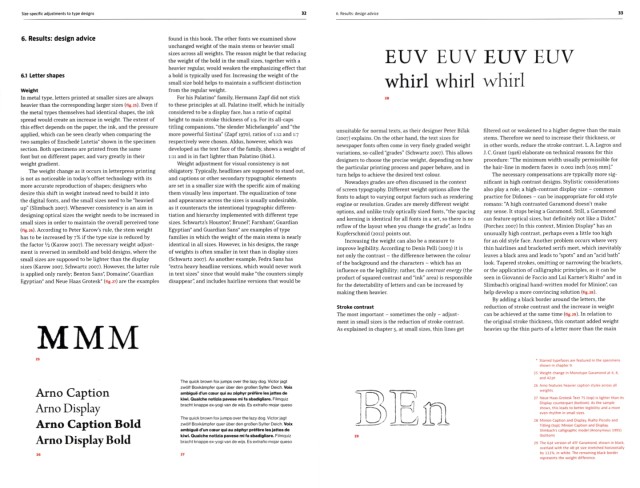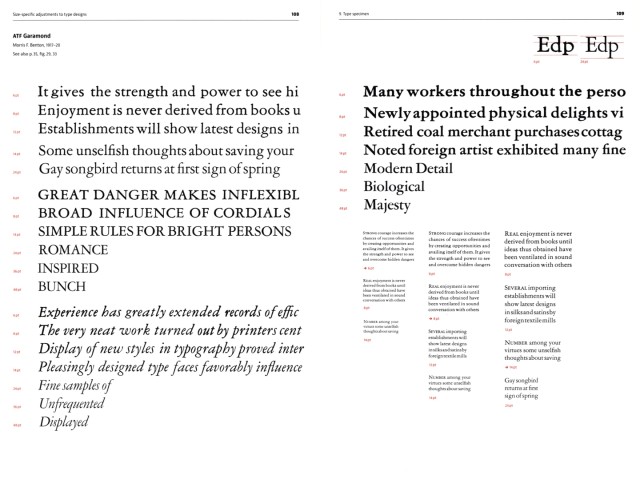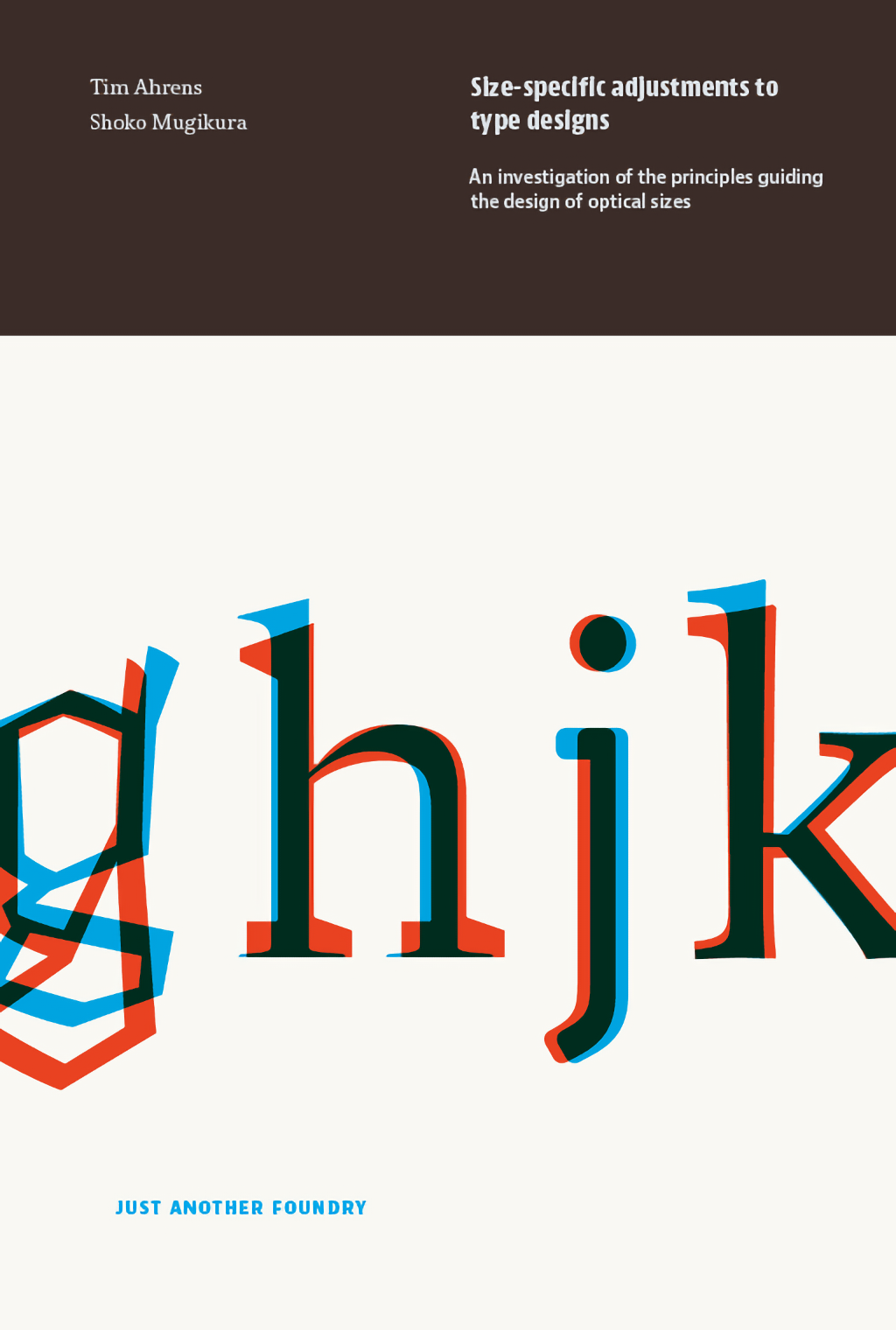
Size-specific adjustments to type designs
Autor: Tim Ahrens & Soho Mugikura
»Jest to nie tyle najlepsza, ale tak naprawdę jedyna znacząca praca na ten intrygujący i złożony temat«. [Thomas Phinney]
»Pomimo specjalistycznego tematu, materiał ten jest cenny nawet dla tych, którzy nigdy nie będą projektować liter ani uruchamiać edytora fontów. Książka jest przydatna także dla typografów i projektantów, którzy dokonują wyboru i używają krojów pism w jakimkolwiek charakterze. Odkrywając sposoby optymalizacji dla konkretnych zastosowań, czytelnicy dowiedzą się wiele więcej o odmianach kształtów znaków, kontraście kreski, proporcjach i odstępach, niż może ich nauczyć niemal każdy inny tekst.«. [Stephen Coles]